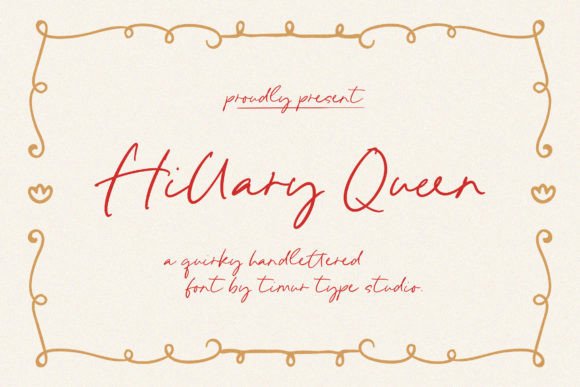
Hillary Queen
Jika Anda mencari aset berkualitas tinggi seperti Hillary Queen, paket premium ini adalah pilihan fantastis untuk proyek kreatif Anda.
Baik Anda membuat produk POD (Print on Demand), undangan pernikahan, atau grafis media sosial, Hillary Queen adalah pilihan yang sangat ideal.